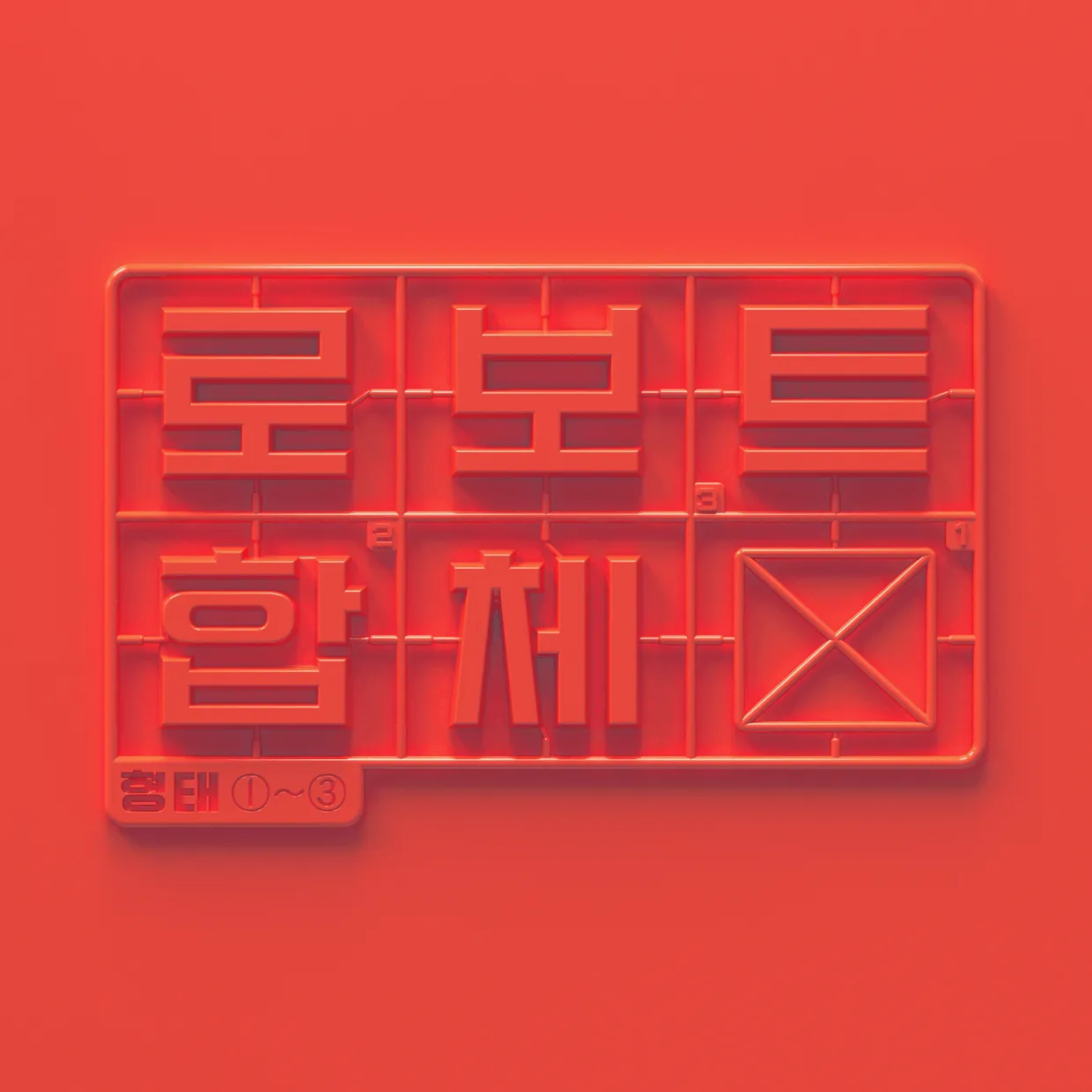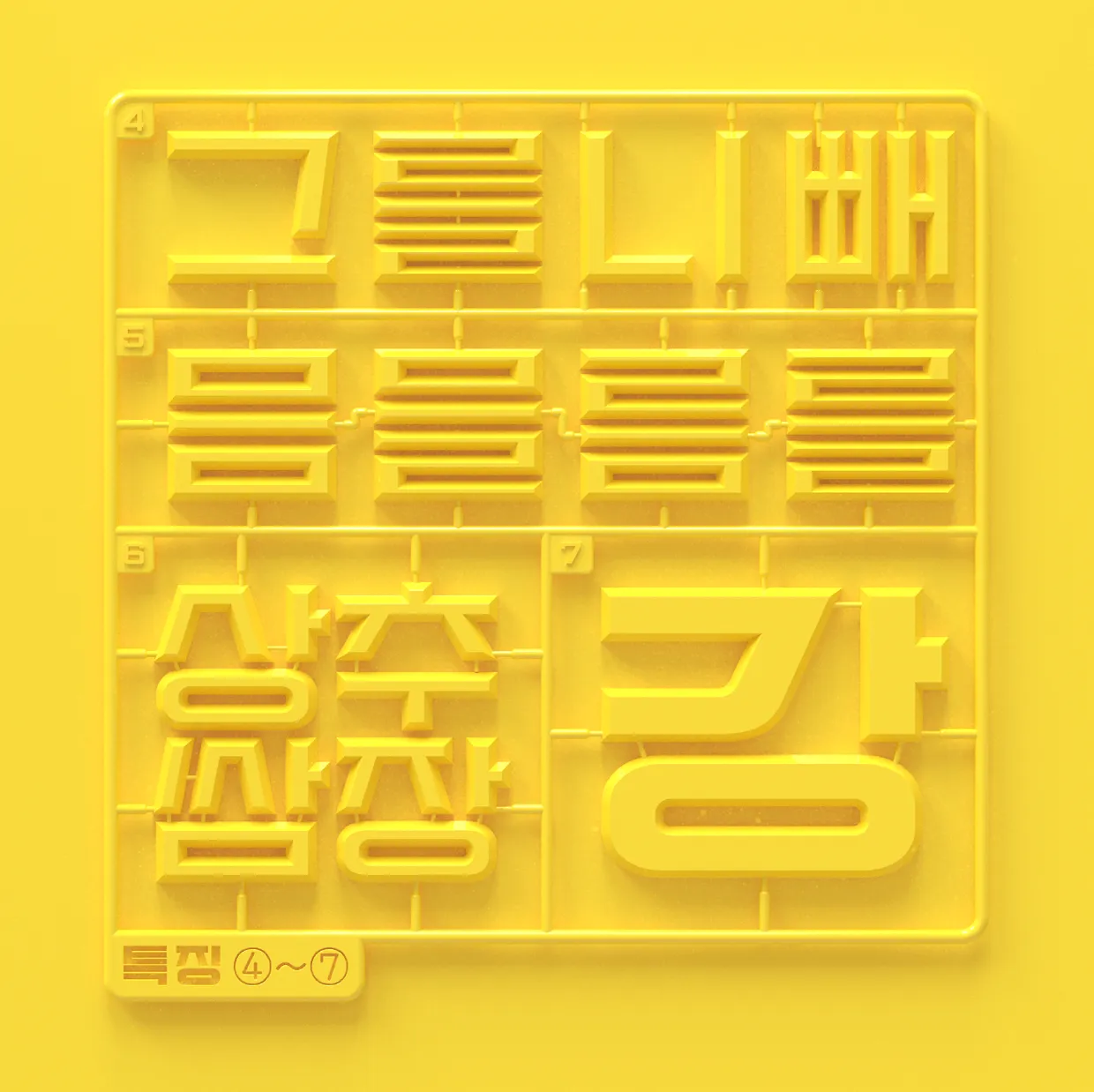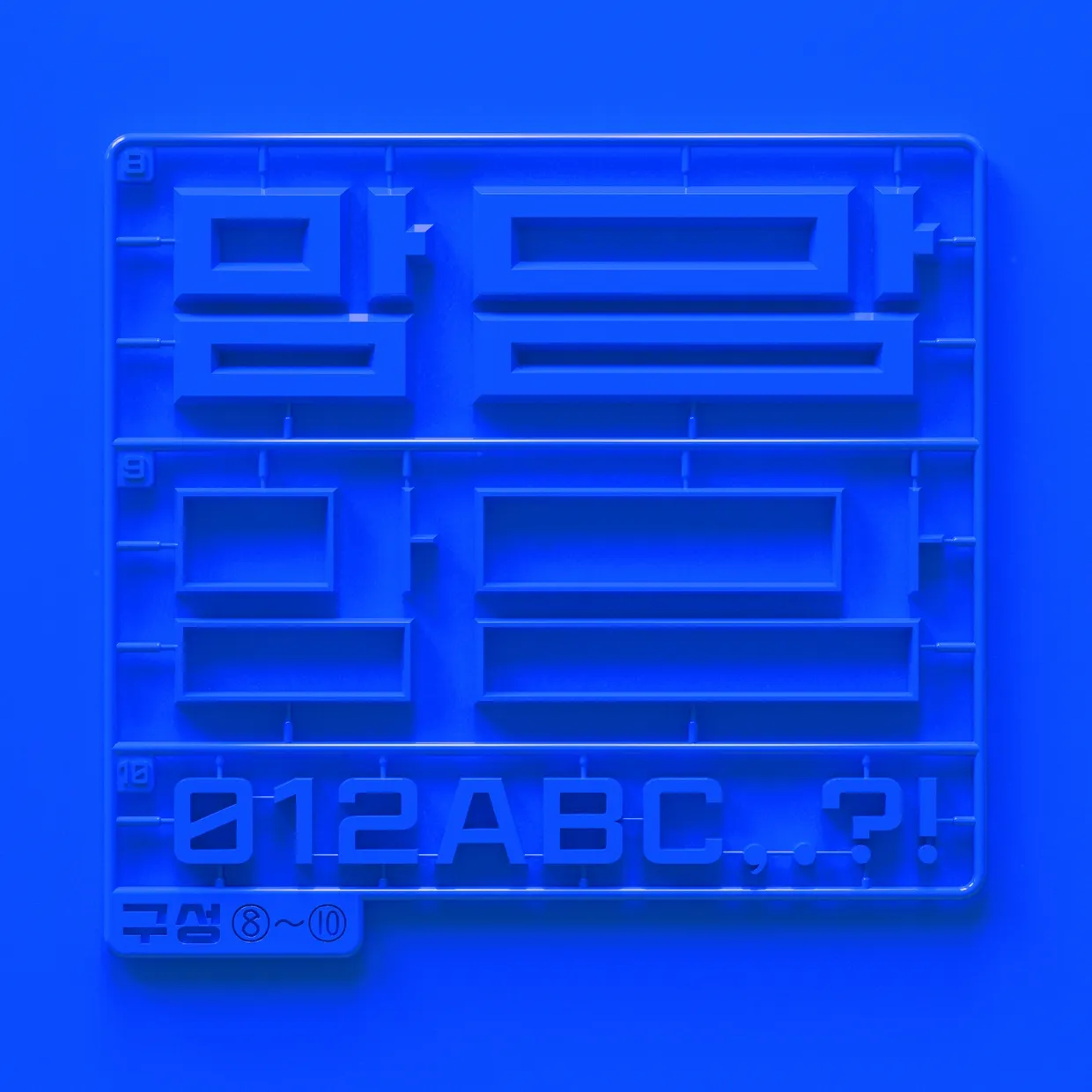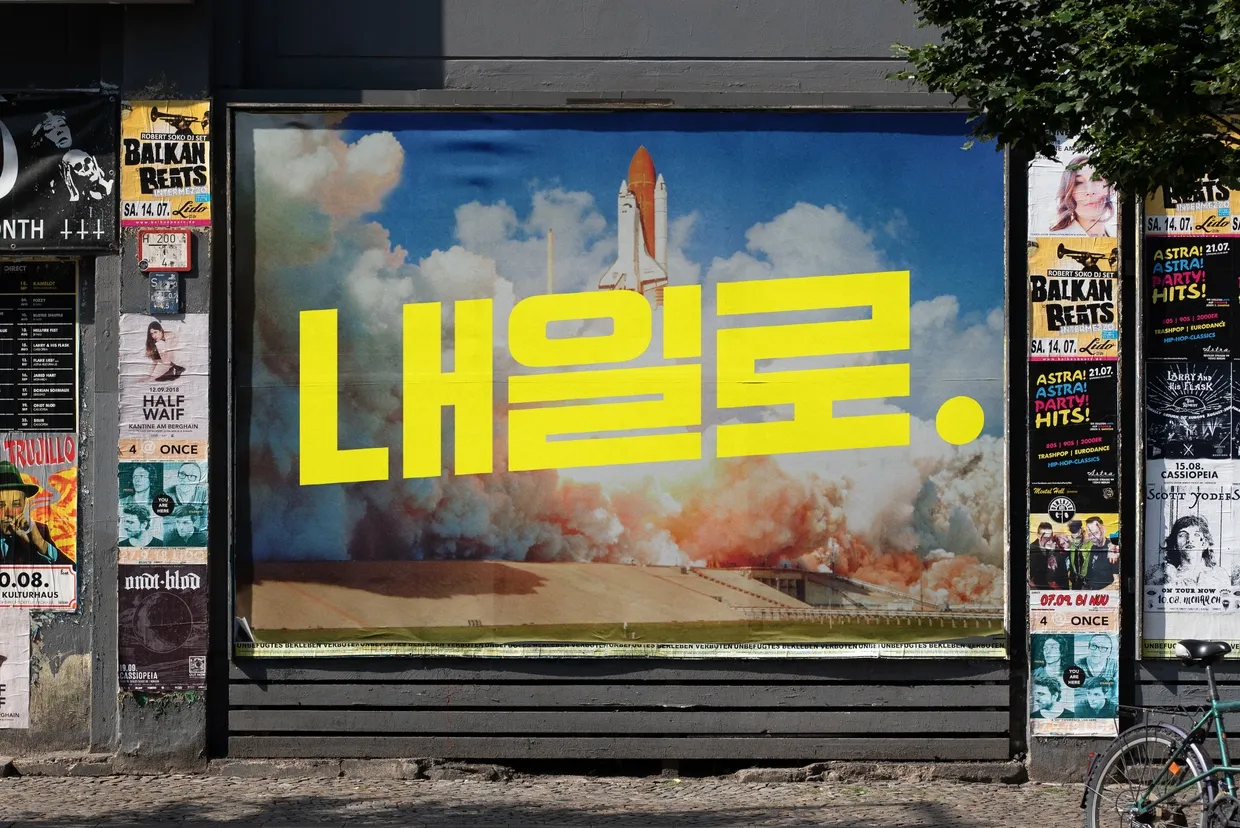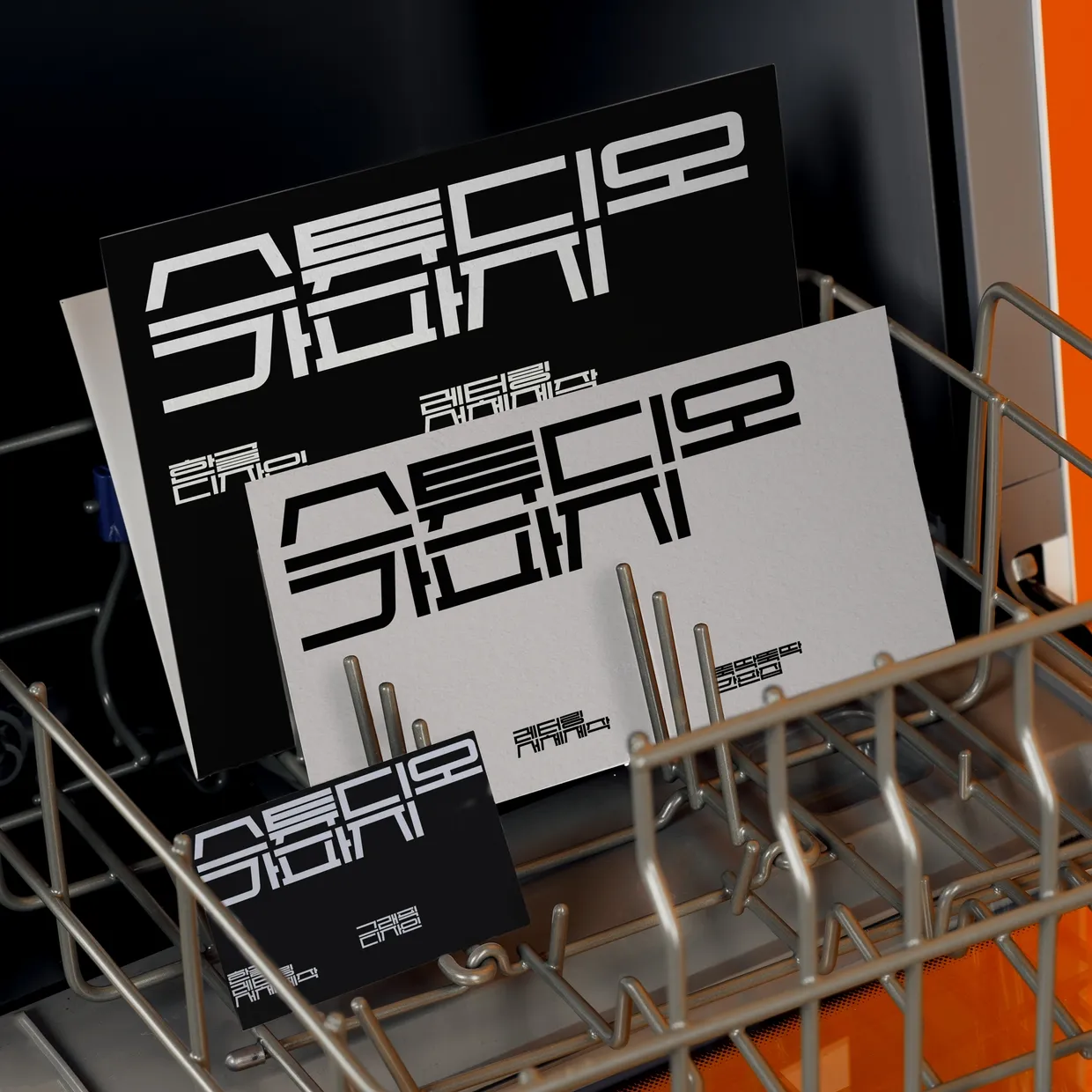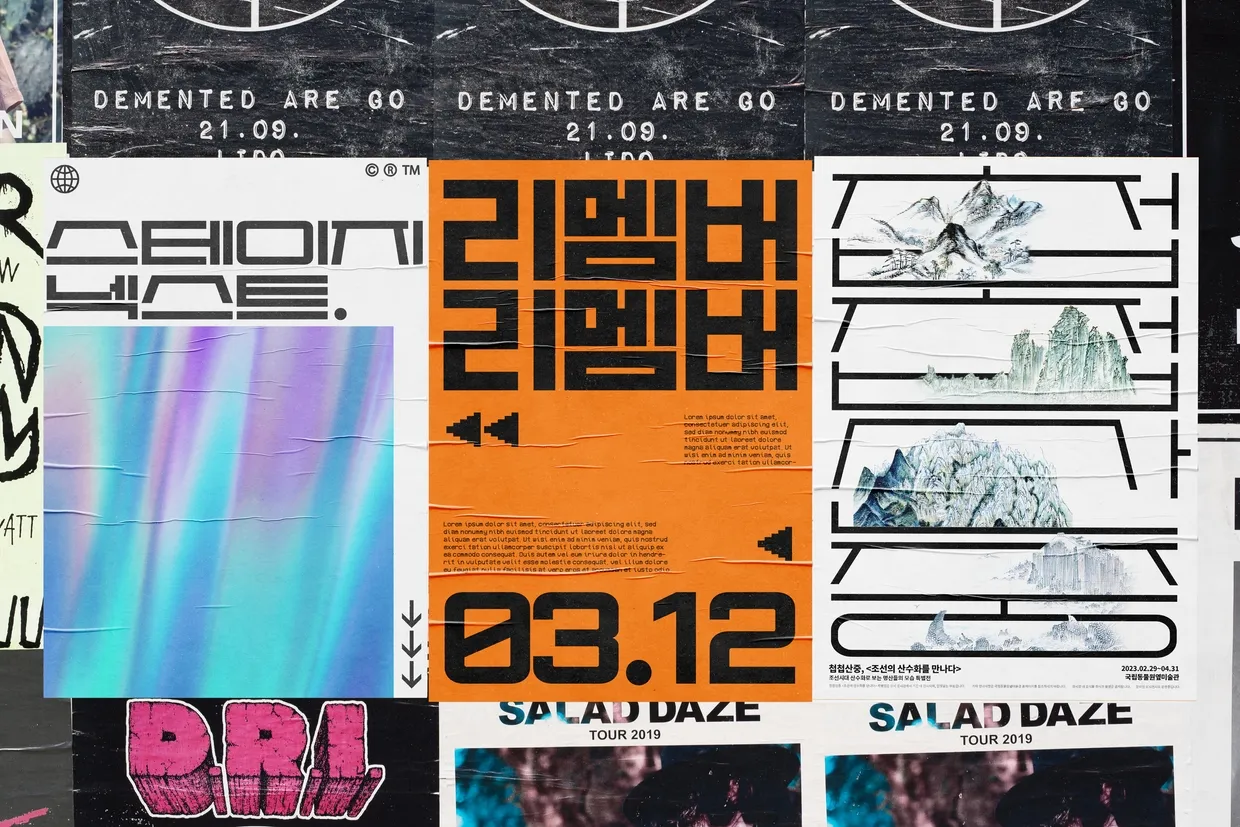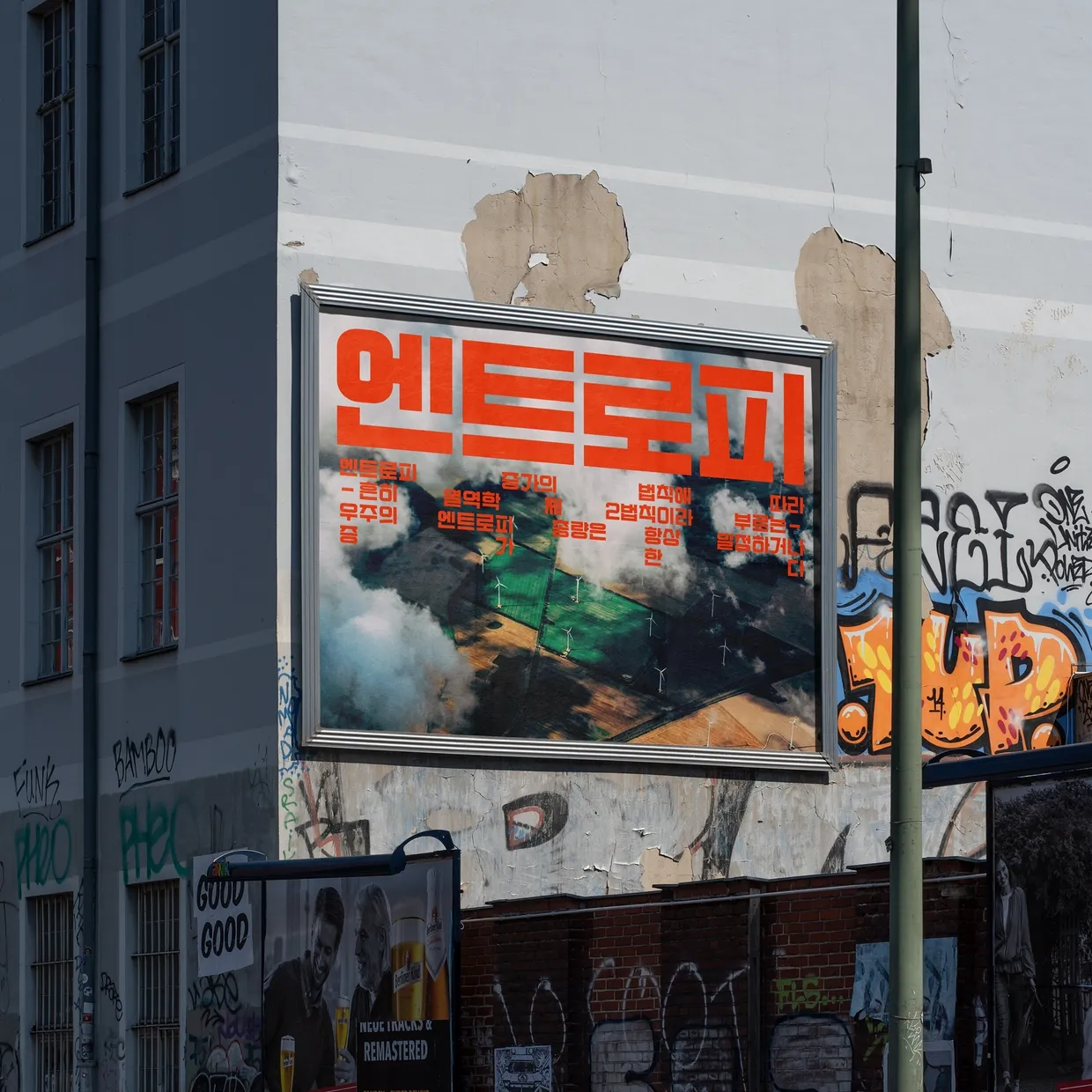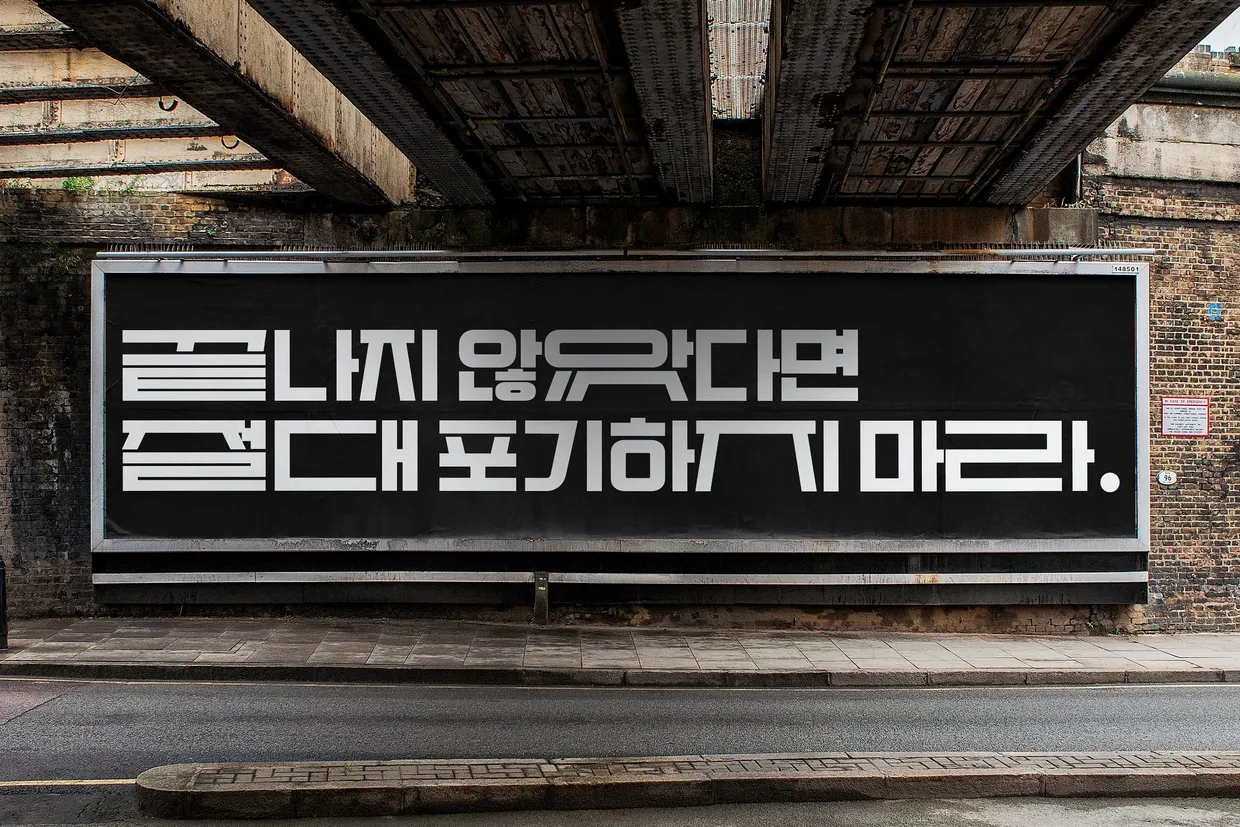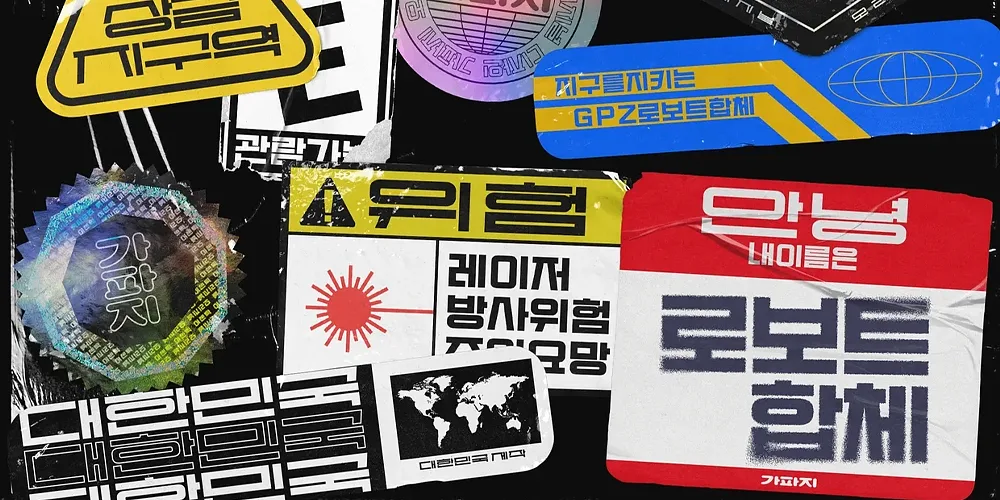
GPZ로보트합체
‘GPZ 로보트합체’는 그 당시 옛날 로보트 만화 제호와 간판 글씨에서 영감을 받은 복고적 인상의 제목용 서체입니다. 로보트 만화처럼 기계적이고 각진 인상에 묵직한 무게감을 더해 주목도가 높은 제목용 서체를 만들고자 했습니다. 기본적으로 획이 굵고 구조가 직관적이어서 제목에 사용하기 적합합니다.
‘GPZ 로보트합체’는 직사각 틀을 꽉 채우도록 설계한 네모꼴 서체입니다. 가로 또는 세로줄기가 밖으로 뻗어나가는 때('ㅎ', 'ㅏ' 등), 사선을 써야하는 때('ㅅ' 등)를 제외하고는 옛날 만화 제호나 포스터 글씨처럼 그대로 틀을 가득 채우도록 했습니다. 획을 교차할 때에도 수평/수직으로 만나게 해 각진 인상을 더했습니다. 따라서 전체적으로 기계적 인상이 강하며 복고풍의 미감을 느낄 수 있습니다.
'GPZ 로보트합체'는 시각적으로 보정을 크게 하지 않은 '기계적'으로 유사한 획 두께를 지니고 있습니다. 공간이 넉넉하다면 완전히 동일한 두께, 부족하다면 낱글자 안의 낱자 안에서는 같은 두께를 지닐 수 있도록 했습니다. 따라서 자소마다 높낮이 차가 생기는데 이를 크게 보정하지 않고 그대로 두었습니다. 세로모임꼴 ‘믐’, ‘믈’, ‘름’, ‘를’을 살펴보면 높이 차가 크게 나는 것을 알 수 있습니다.
'GPZ 로보트합체'는 독특한 시옷, 기역계열 자소를 가지고 있습니다. 시옷계열(ㅅ, ㅆ, ㅈ, ㅉ, ㅊ)은 로보트가 다리로 우뚝 선 것처럼 사선을 세우듯이 표현하고, 쌍자음의 경우에는 획을 일부 생략해 표현했습니다. 기역계열 자소(ㄱ, ㅋ, ㄲ)와 이응계열(ㅇ, ㅎ) 자소는 옛날 간판에서 종종 보이던 모습처럼 보통 곡선인 구간을 직선과 곡선의 조합으로 사용해 직선적 인상과 복고적 느낌을 더했습니다.
‘GPZ 로보트합체’는 굵기에 따라 라이트(Light)와 볼드(Bold), 너비에 따라 베이직(Basic)과 익스팬디드(Expanded)로 구분되며, 총 네 가지(Light Basic, Light Expanded, Bold Basic, Bold Expanded)로 구성돼 있습니다.